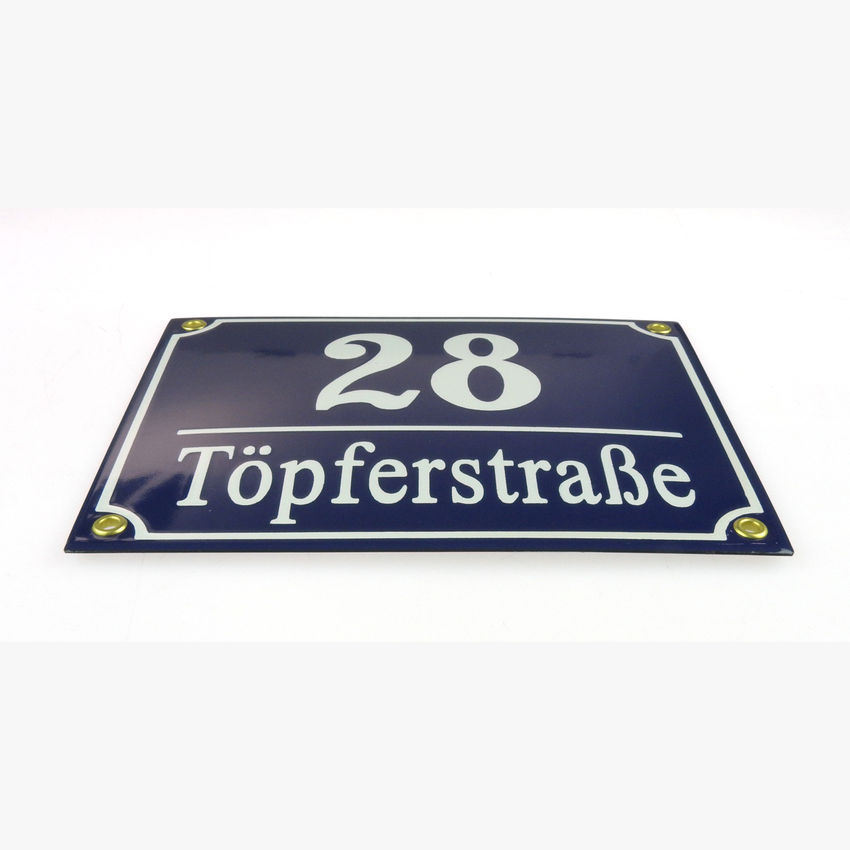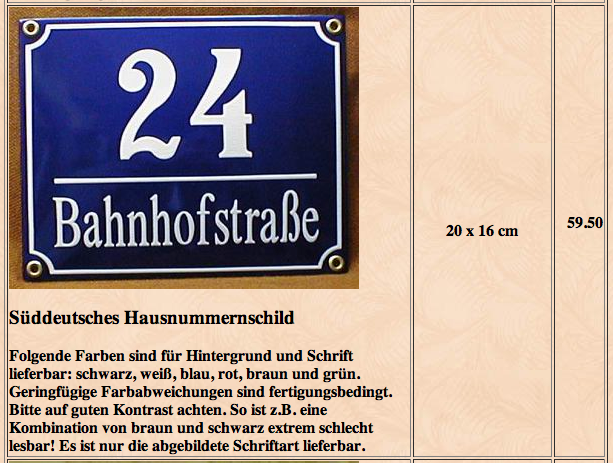
Emaille Hausnummernschild
kann mir vielleicht jemand verraten welche Font in etwa sich auf diesem Schild befindet?
Eine ähnlich passende würde mir auch schon weiterhelfen. Habt vielen lieben Dank!
… Bei den Ziffern muss ich passen. Eine 4, die oben eine Serife hat, ist mir so noch nicht untergekommen.
Es gibt vereinzelt schon welche …
Frag doch mal den Hersteller;-)
Es gibt vereinzelt schon welche …
Chesterfield Antique von Alan Meeks (1977, kommerzielle Schrift)
Chelsea von Typographer Mediengestaltung AKA Dieter Steffmann (2000, Freeware)
Tipp: Diese Schrift hat auch Zierbuchstaben (alternate characters).
Cheboygan von Christine Mauerkirchner und Rainer Grunert Schwalbach AKA PrimaFont (1995)